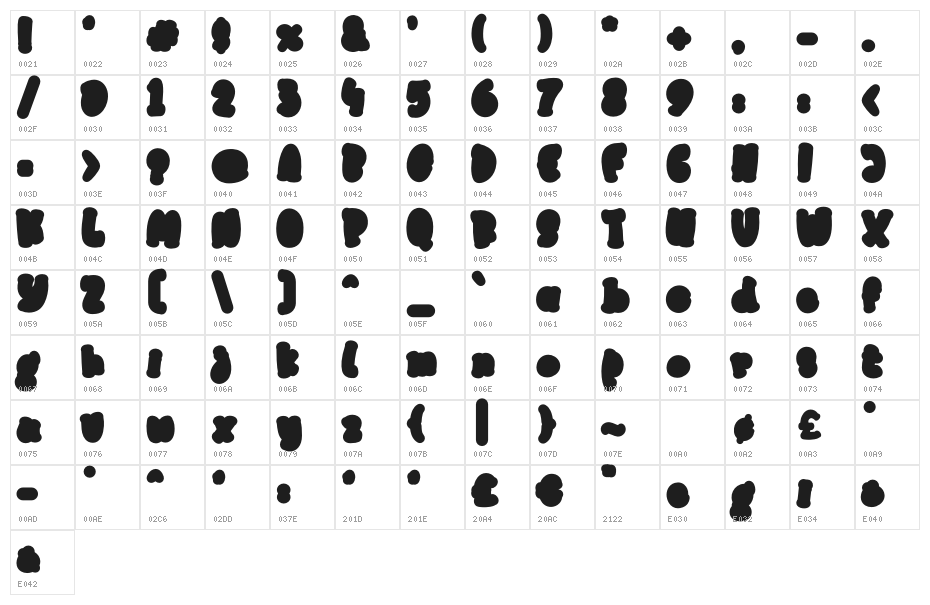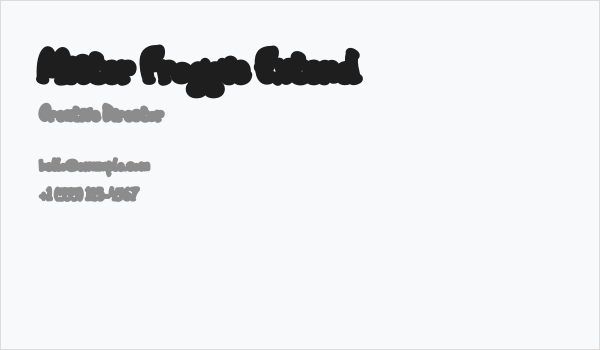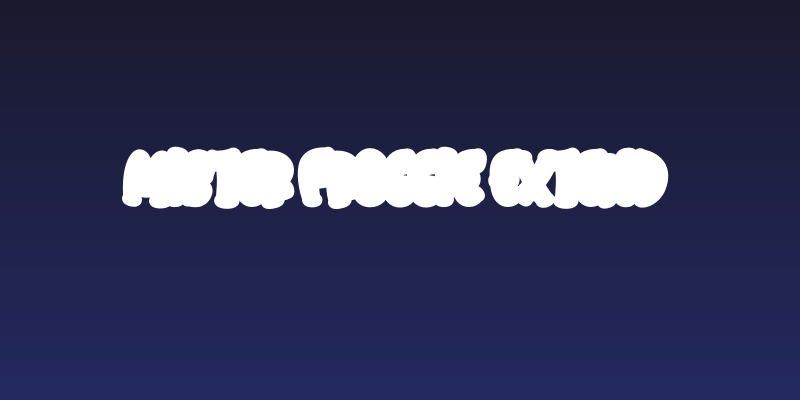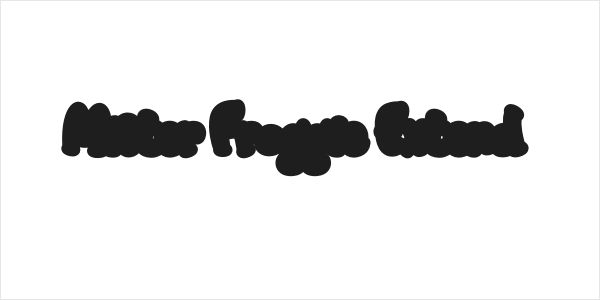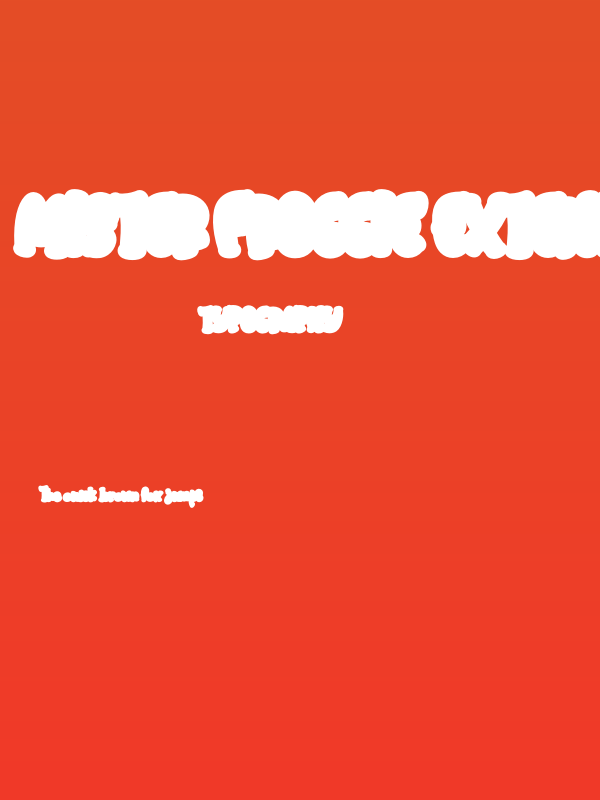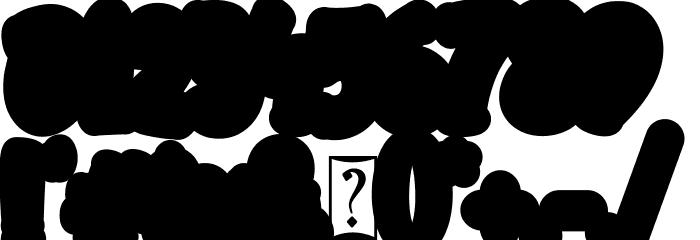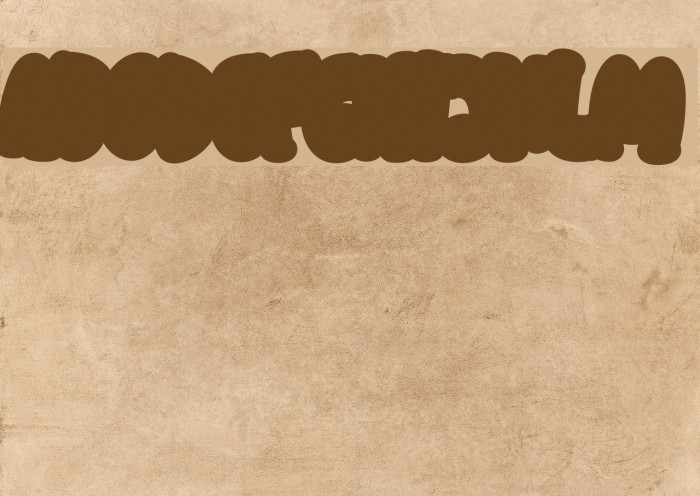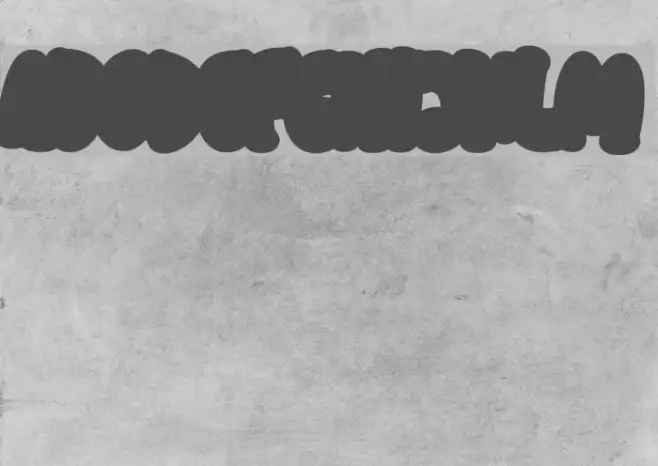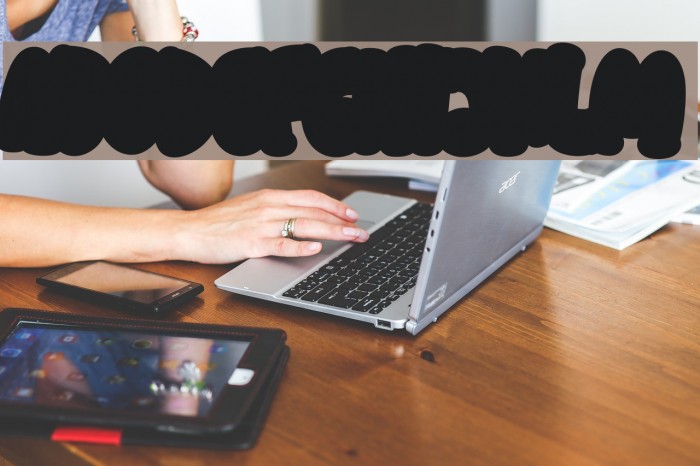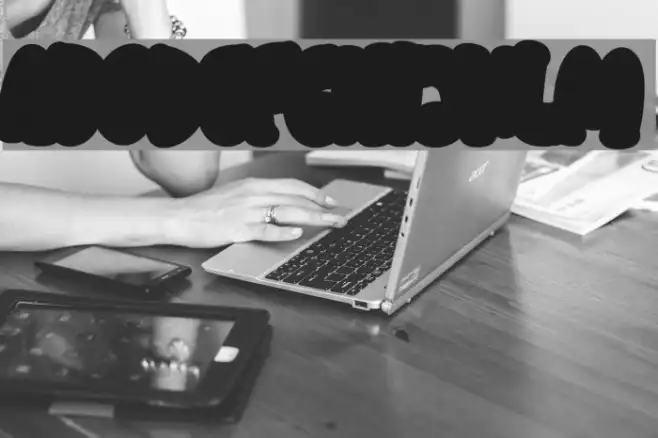
Mister Froggie Extend Font
| Ancho | Expanded |
| Estilo general | Playful, Whimsical |
| Caso de uso | Logos, Headlines, Posters |
| Proyectos propuestos | Ideal for children's book covers, playful branding, party invitations, and creative posters. |